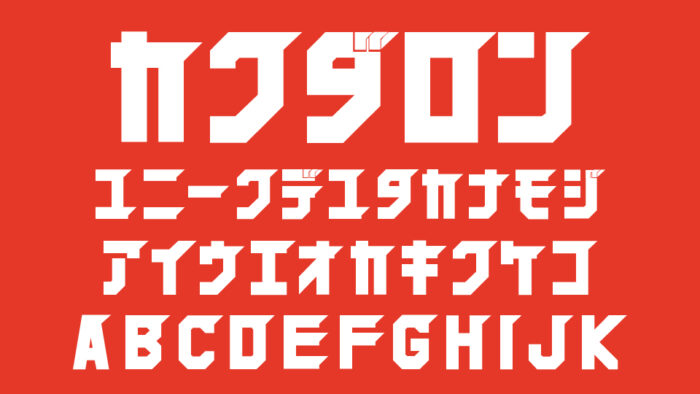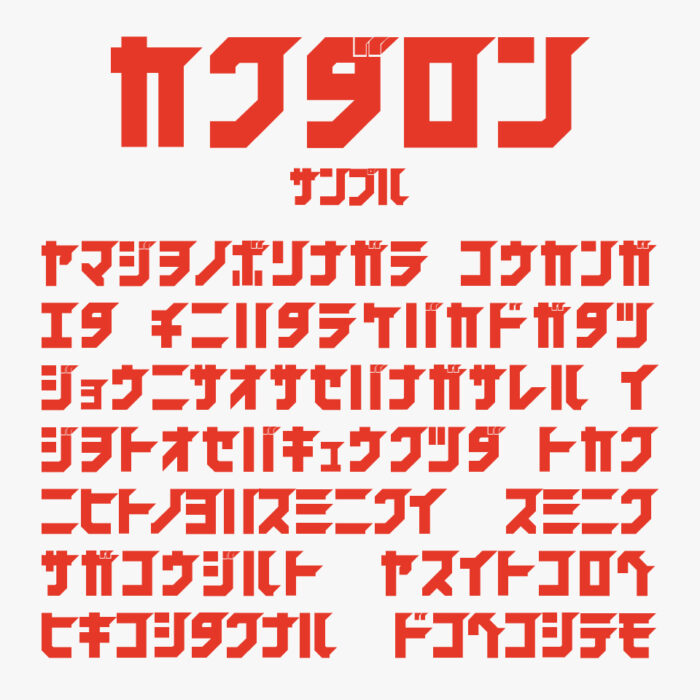
カクダロン
カクダロンフォントは、スピード感を感じる装飾と、無骨で角張ったフォルムが特徴的なデザインフォントです。
直線と直角でどっしりとした構成されたデザインなので、映画タイトルロゴやポスター、ラベルなどに使えば、力強さとインパクトを感じるフォントです。
収録文字は、カタカナ・アルファベット・数字・記号が収録されています。